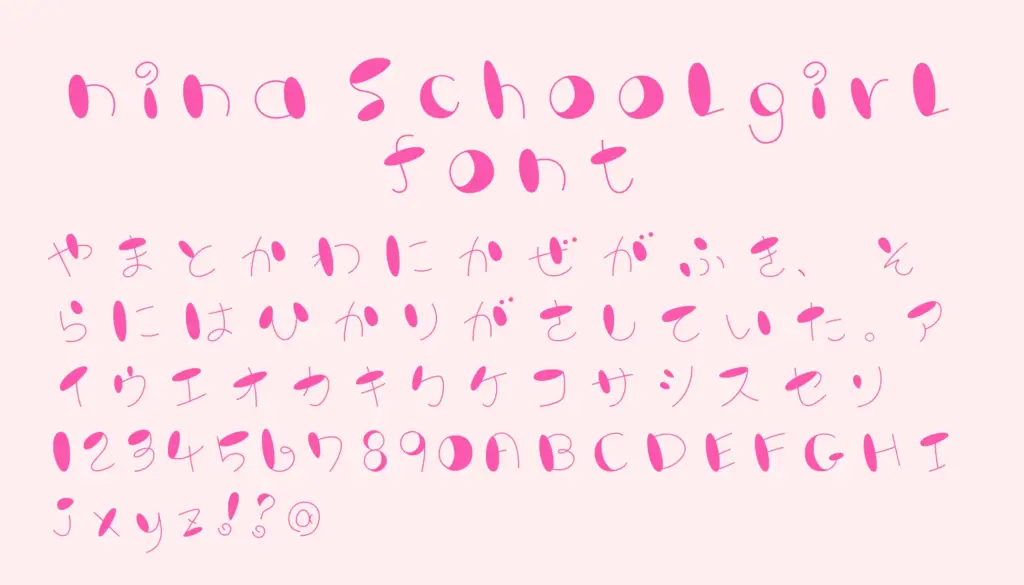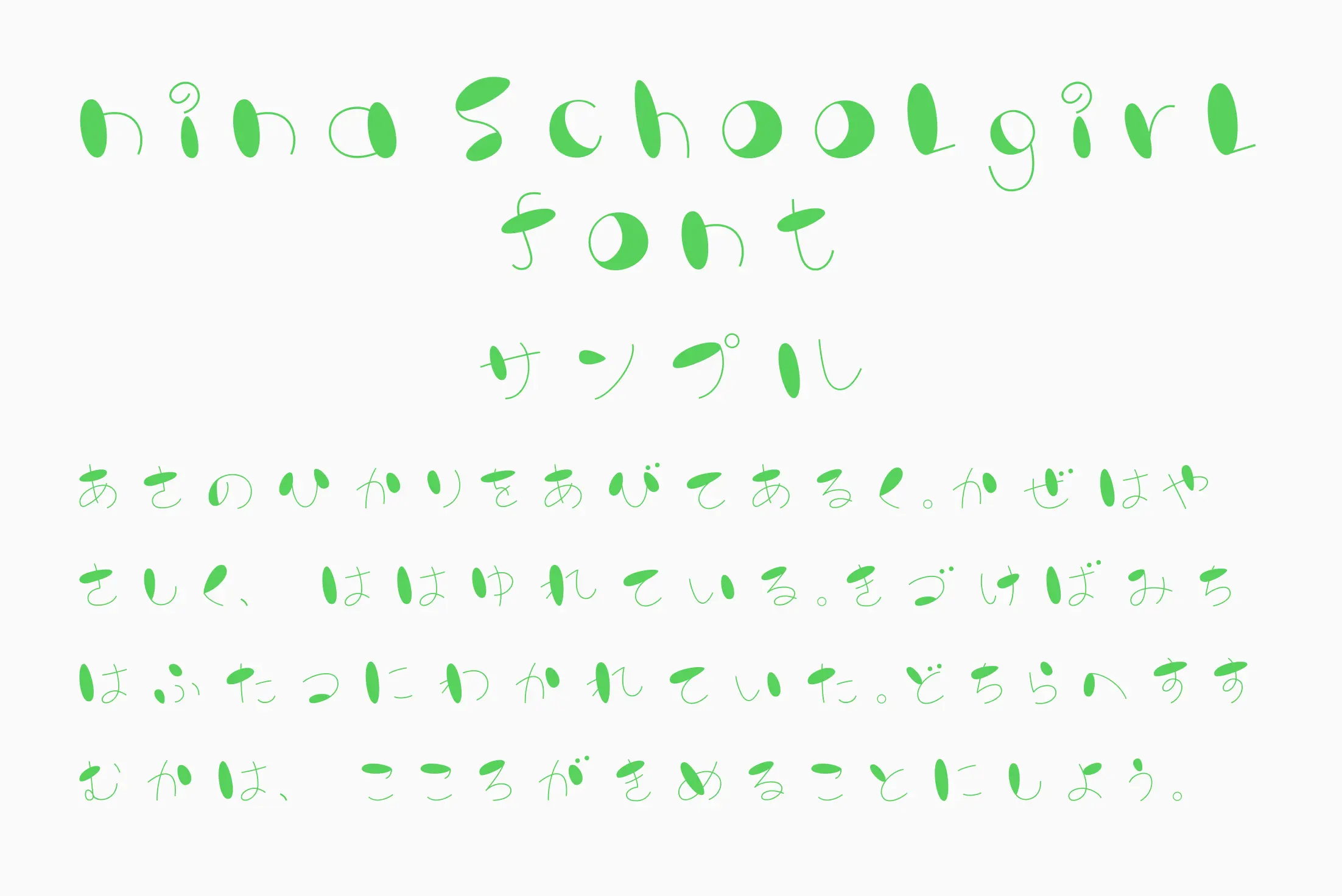
女子高生のノート文字を思わせる、素朴で自然な手書き風フォントです。細身のストロークに軽やかな揺らぎがあり、親しみやすくカジュアルな印象を与えます。勉強系コンテンツや日常系デザイン、SNS投稿、YouTubeサムネイル、同人誌の台詞などに最適です。
nina_Schoolgirl_font
収録文字 | カタカナ・ひらがな・英字・数字・記号 |